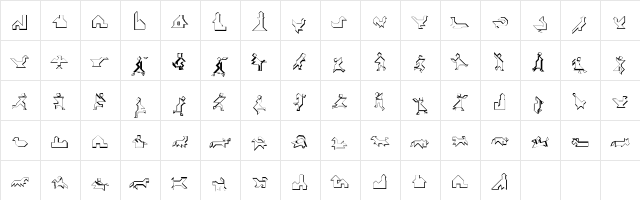
Copyright: 22.8.93 anfred Klein. 1 Quadrat, ein Parallelogramm, fuenf dreiecke in drei groessen: ein jahrtausendealtes chinesisches Formenspiel, hier zum ersten Mal fie Typografie nutzbar gemacht.